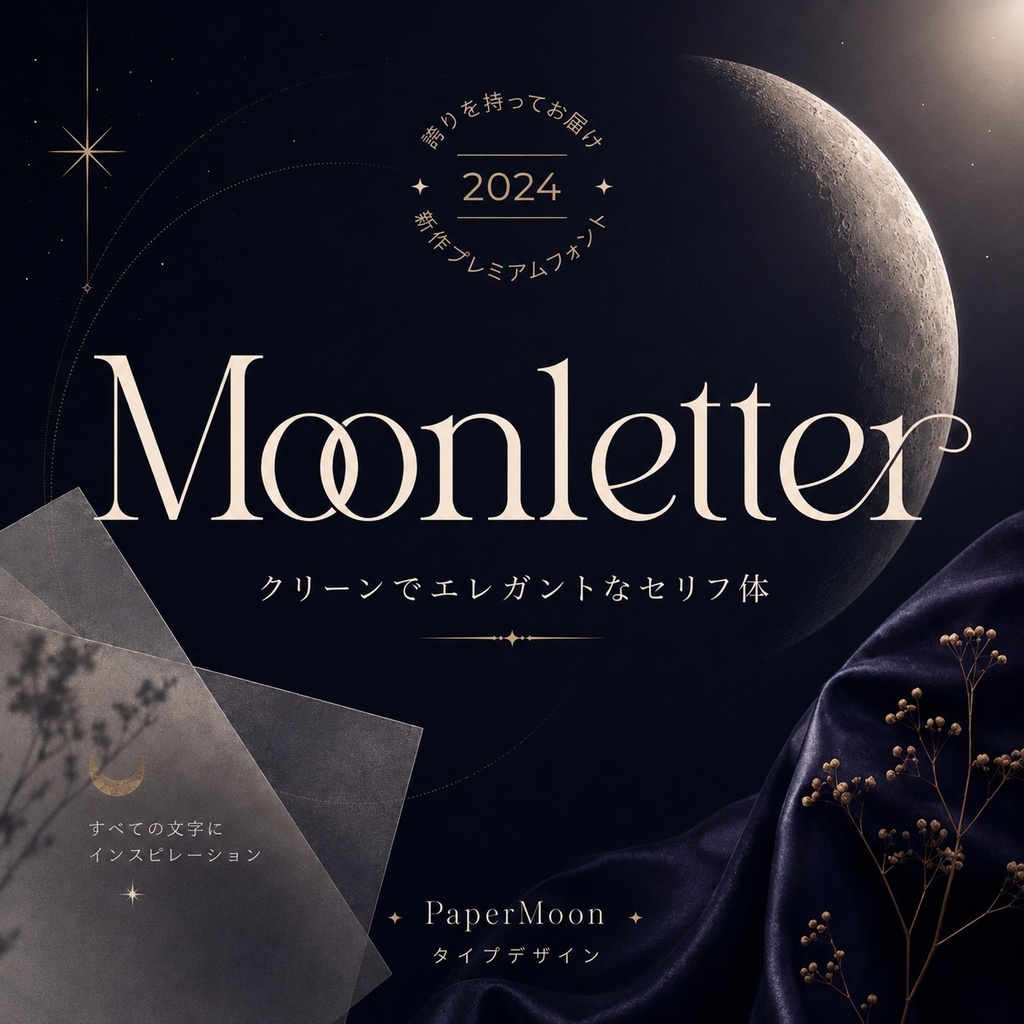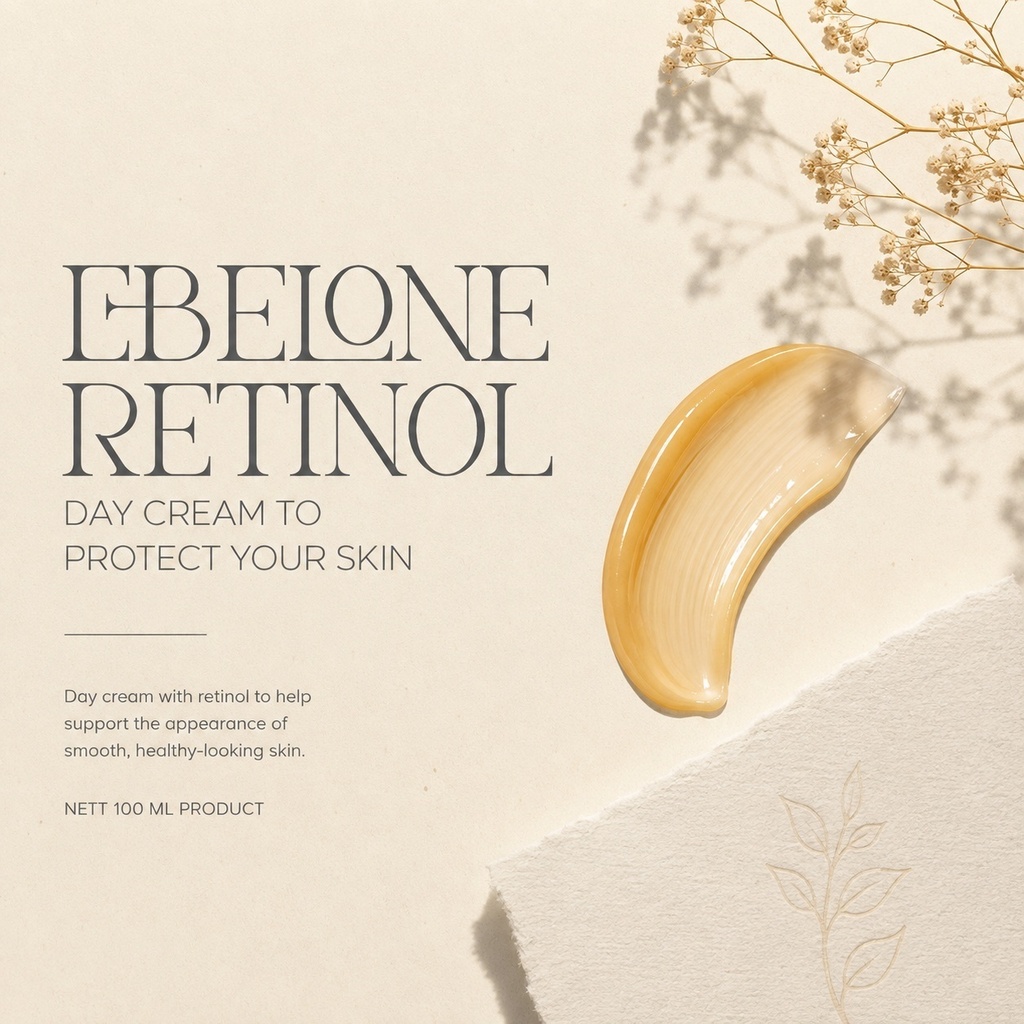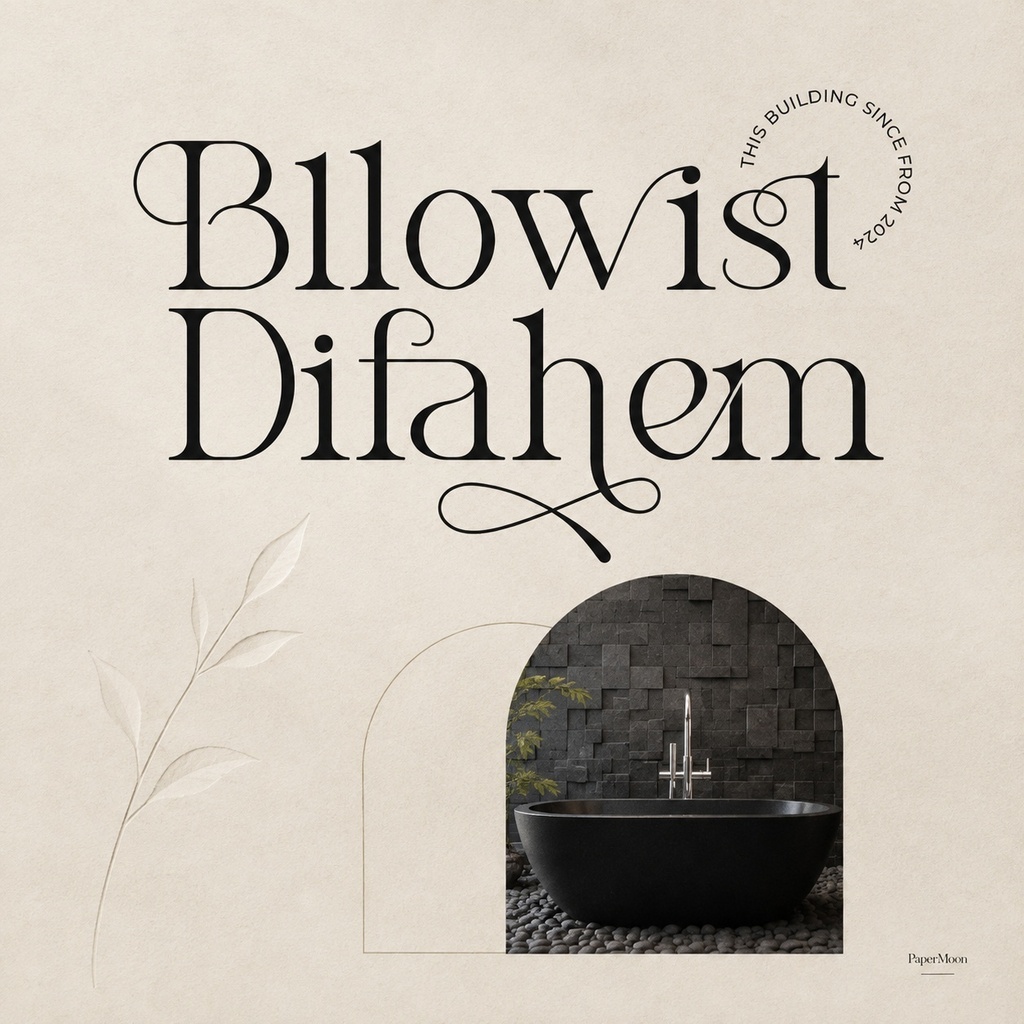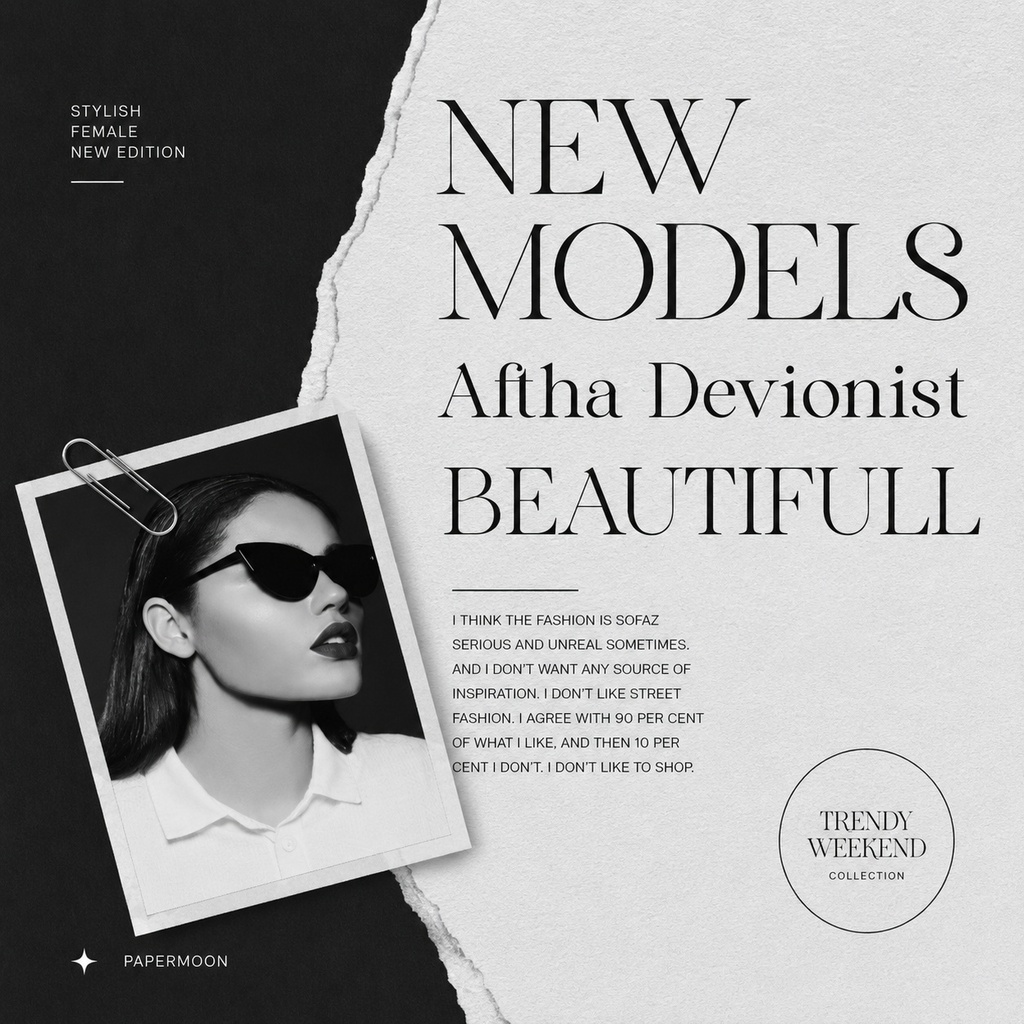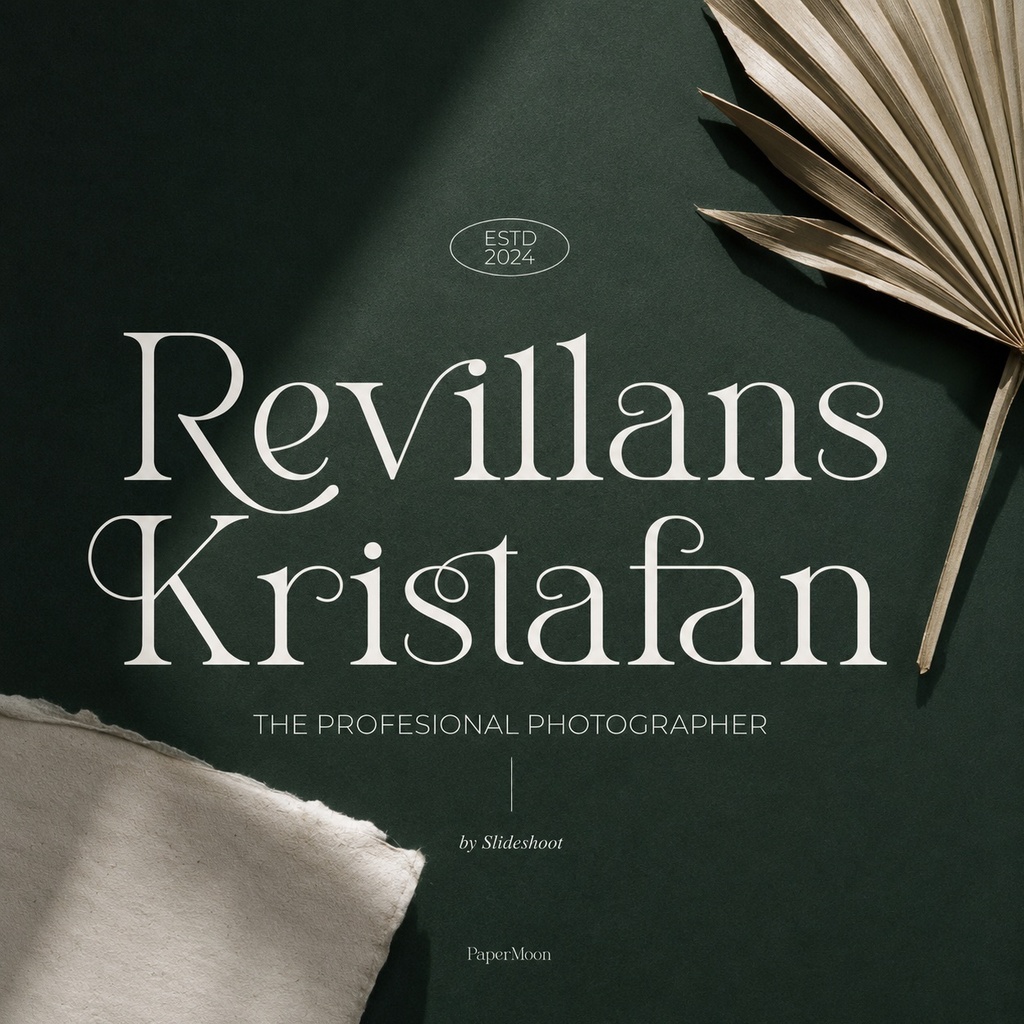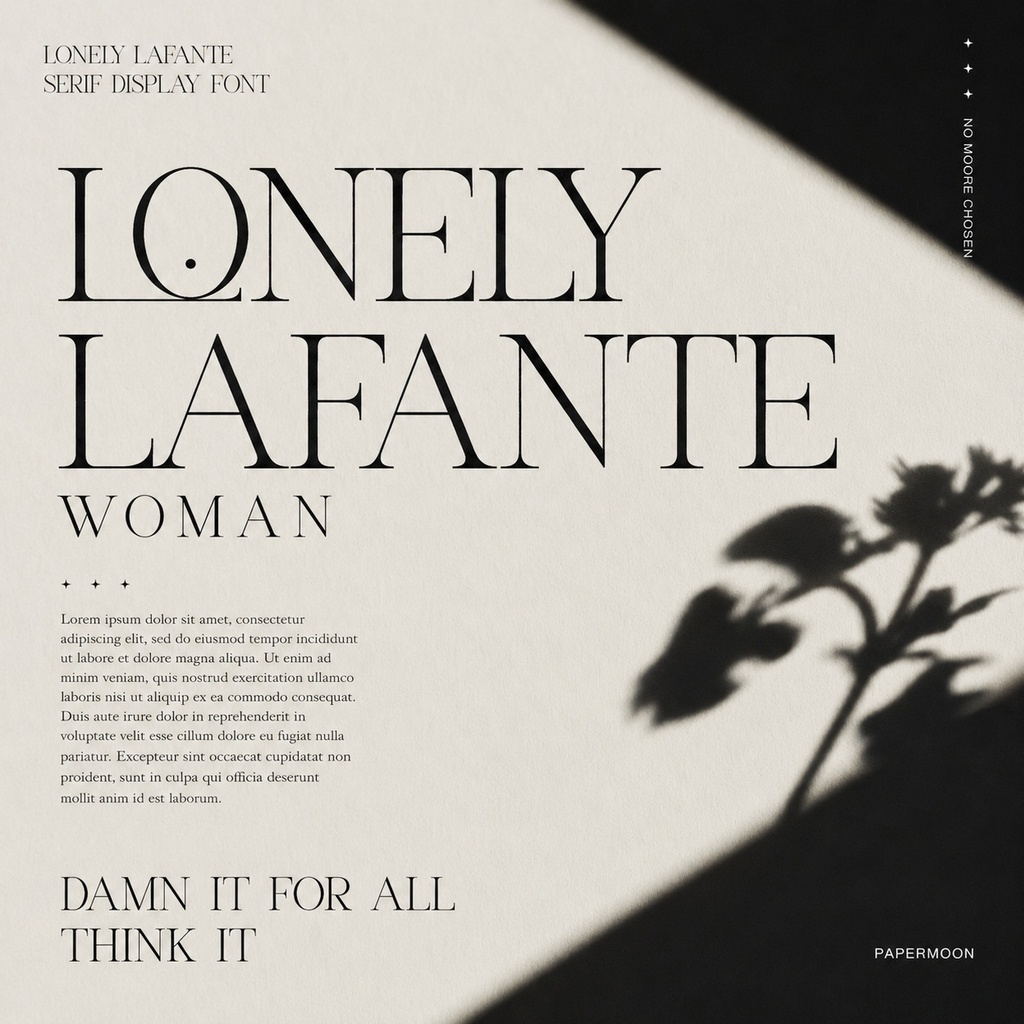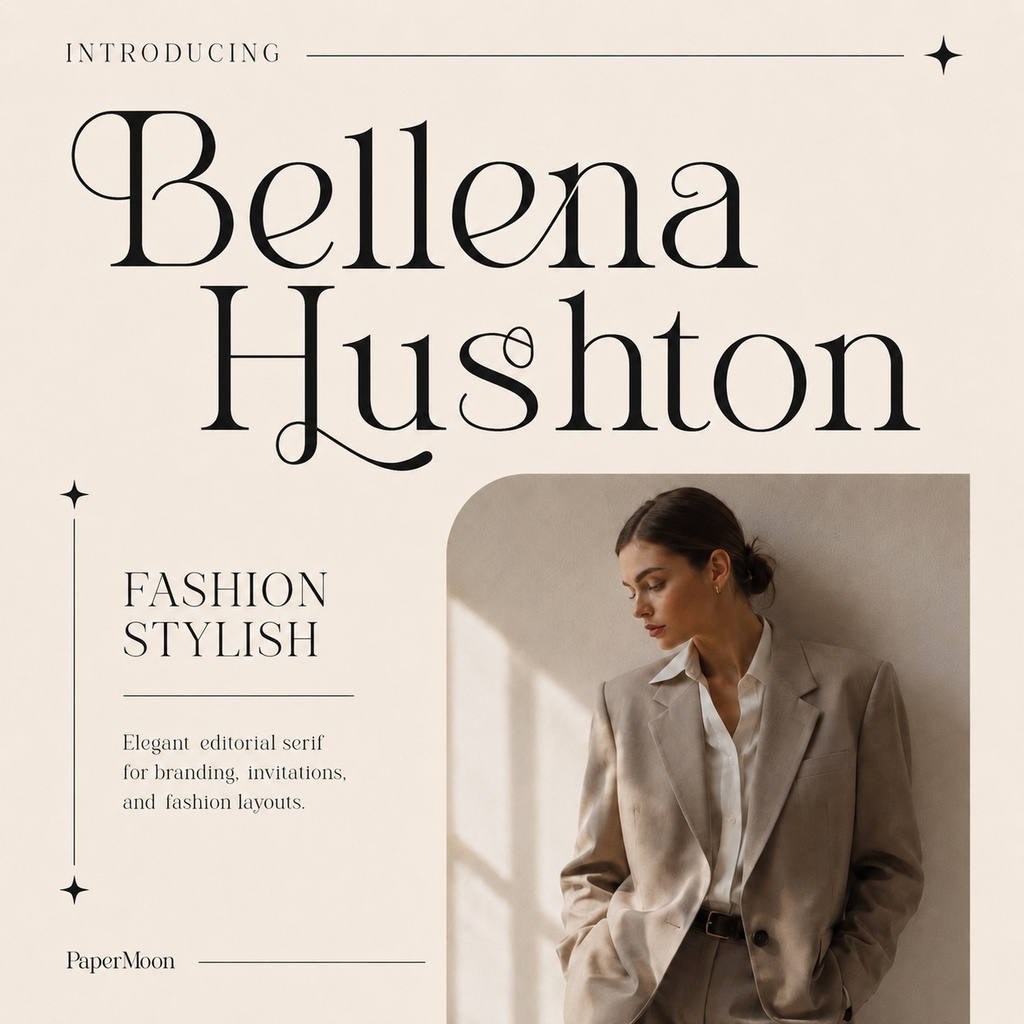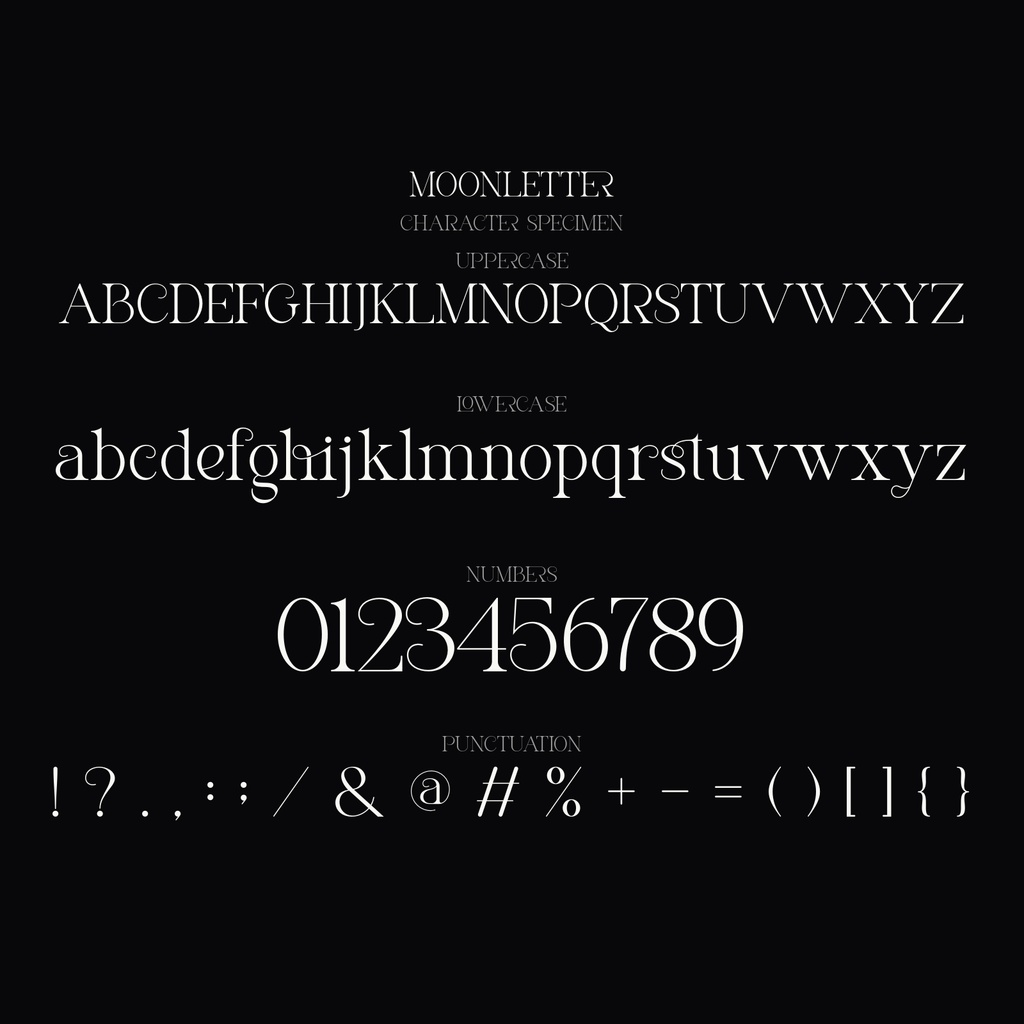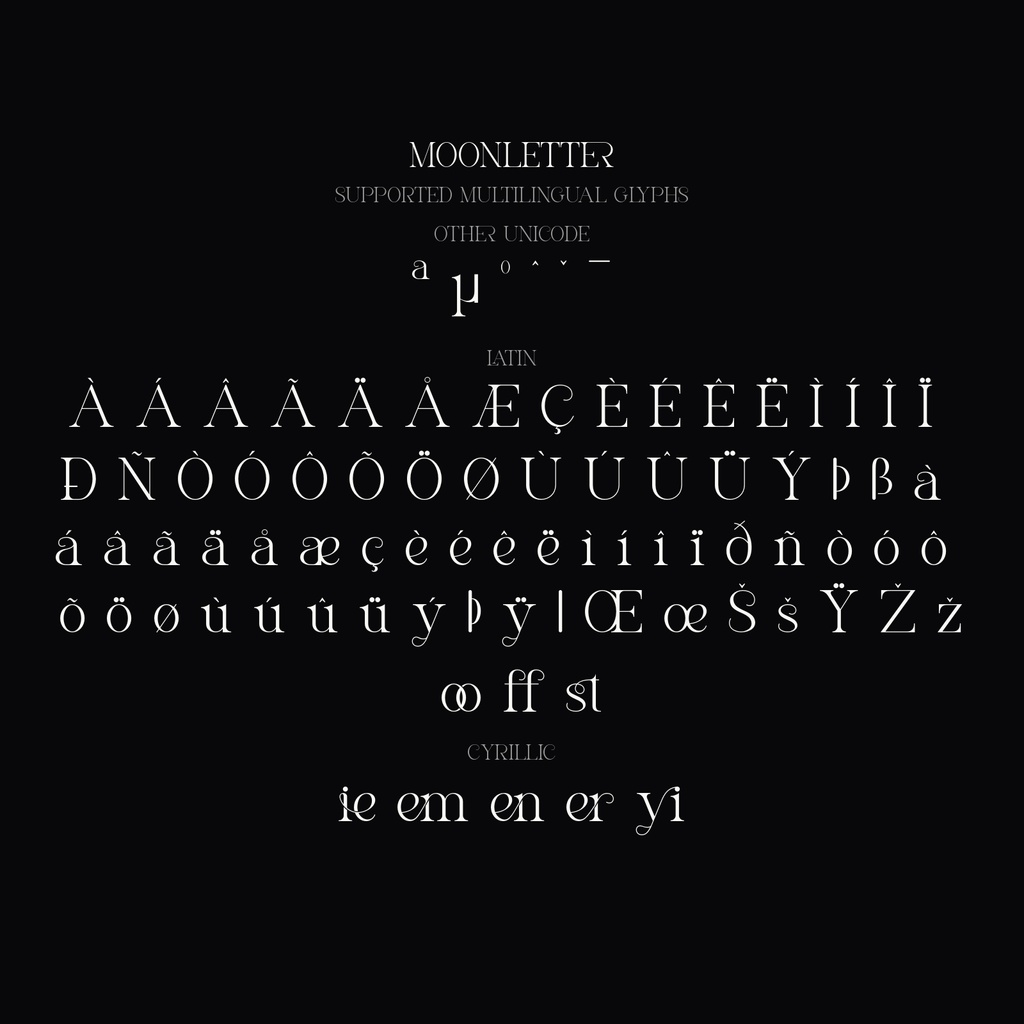
Moonletter | 高級感のある欧文セリフフォント | ロゴ・招待状・ブランド向け
Moonletterは、高級感と洗練された雰囲気を表現できるエレガントな欧文セリフフォントです。スタイリッシュな字形のアクセントとリガチャを備え、短い言葉や名前に上品で印象的な表情を加えます。 招待状、会社のロゴ、映画タイトルや作品名、名刺、書籍タイトル、ブランド名など、品格を重視するデザインにおすすめです。ブランドのロゴや見出し、印刷物、その他のデザイン制作にもご利用いただけます。 ### 収録内容 - Moonletter - スタイリッシュな字形のアクセント - リガチャ - 大文字・小文字、数字、句読点 ### 対応文字 大文字・小文字、数字、句読点を収録した英字向けフォントです。日本語文字の収録については、購入前にご確認ください。 ### 用途 招待状、会社ロゴ、ブランドロゴ、映画タイトル、作品名、名刺、書籍タイトル、ブランド名、見出しなど。 ### 形式 デスクトップ用:OTF / TTF ウェブ用:WOFF / WOFF2 ### 対応環境 PCおよびMacで使用できます。インストール後、Adobe Illustrator、Adobe Photoshop、Adobe InDesign、Microsoft Wordなどのフォント対応ソフトでご利用いただけます。リガチャや字形のアクセントの表示方法は、アプリケーションによって異なる場合があります。 ### 利用許諾 商用利用版と個人利用版の2種類があります。具体的な利用範囲、再配布、埋め込み、再販などの条件は、購入する各バリアントに付属するライセンス本文をご確認ください。 Moonletterで、日常の文字組みに静かな華やかさと洗練された印象を加えてください。